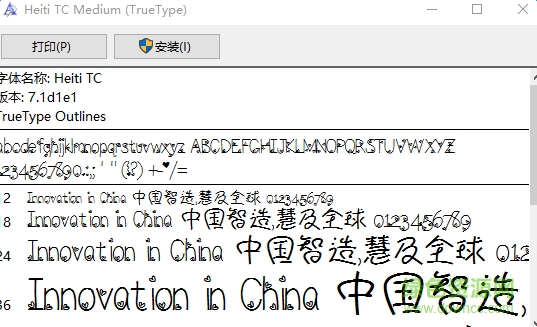
瀟灑自在字體是一款很有特色的電腦個性字體,就像這款字體的名字所寫一樣它是瀟灑自在、沒有任何規(guī)律的字體,所以寫出來的字也是很灑脫的,喜歡這款字體的朋友可以來綠色資源網(wǎng)下載。
瀟灑自在字體這款字體是真的很不錯,寫出來的字效果很不錯,可以用于很多方面,藝術(shù)設(shè)計、廣告設(shè)計等都是可以的,歡迎大家來綠色資源網(wǎng)下載使用。